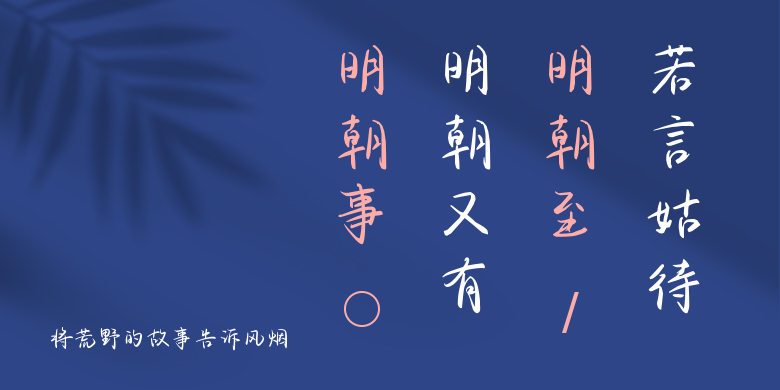
将荒野的故事告诉风烟
将荒野的故事告诉风烟,这款字体结构工整、笔画清晰,兼顾美观与易读性,适用于标题、正文、海报、包装、LOGO 等多种场景。字形优雅稳定,风格百搭耐看,适配日常排版与创意设计,让文字呈现更舒适、更具质感。将荒野的故事告诉风烟一笔一画,皆是细节,以均衡的比例、流畅的线条打造舒适视觉体验,字形端正大气,风格简约现代。无论是商业设计、品牌宣传还是日常排版,都能轻松驾驭,让文字更有格调与力量。将荒野的故事告诉风烟字体下载。